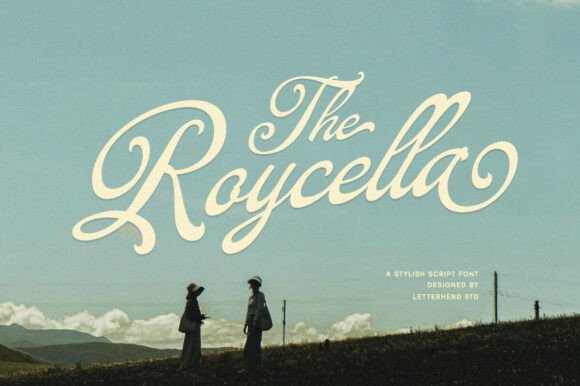
The Roycella Script
Trouver les bons éléments de conception peut être un défi, mais The Roycella Script propose une collection exceptionnelle qui rehausse instantanément votre travail.
Conçu avec précision, The Roycella Script offre des vecteurs nets, une typographie fluide et une licence commerciale pour une tranquillité d'esprit.
Que vous créiez des produits POD (impression à la demande), des invitations de mariage ou des visuels pour les réseaux sociaux, The Roycella Script est un choix idéal.